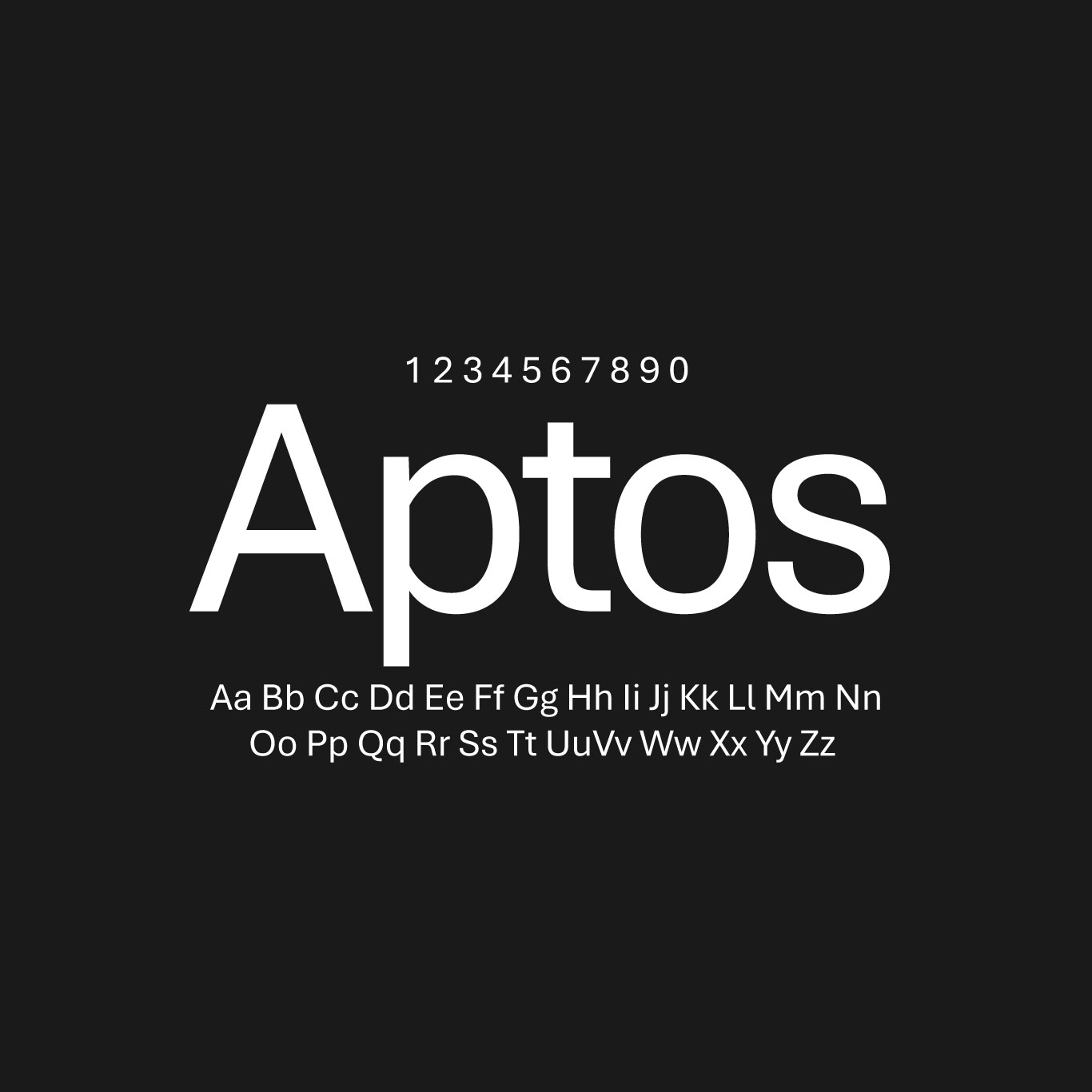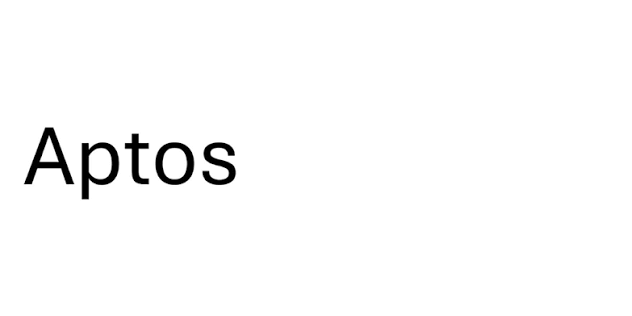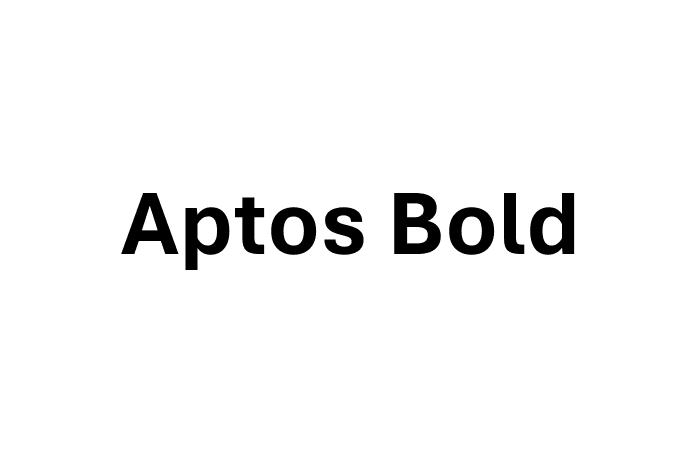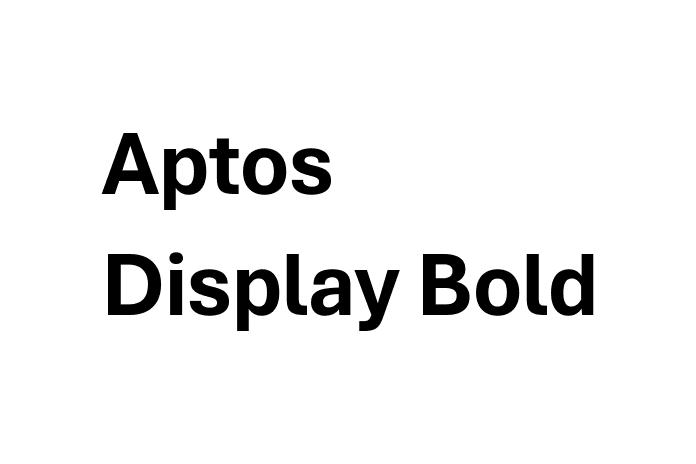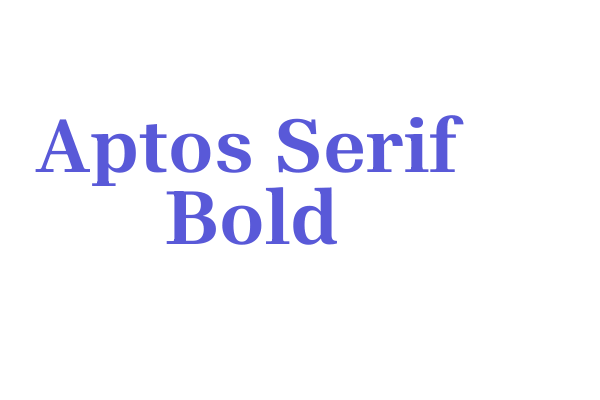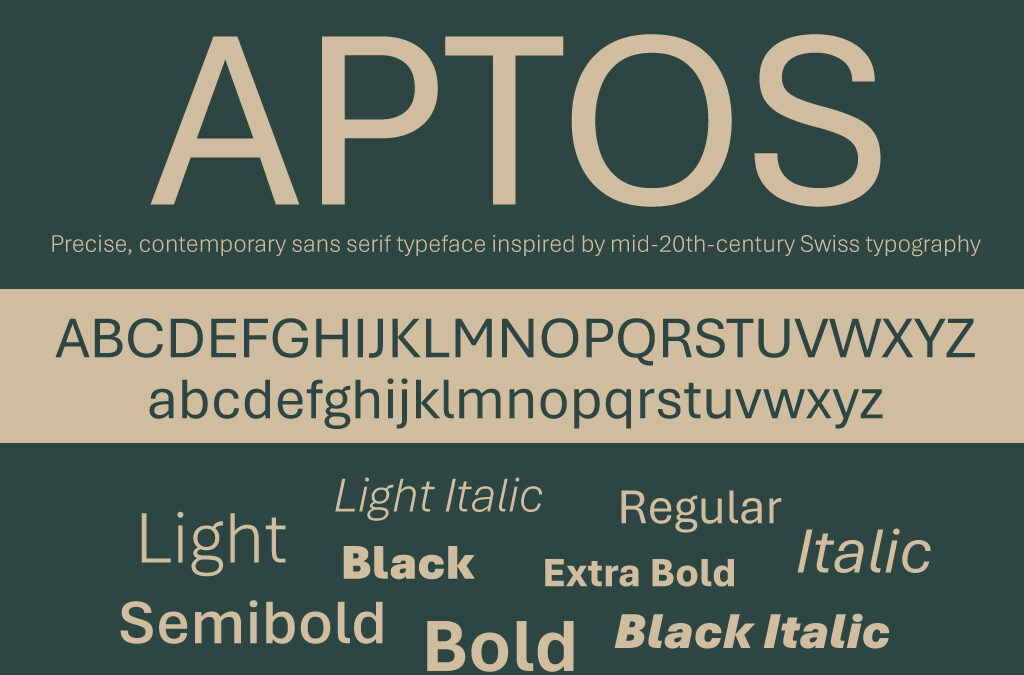
Aptos là hệ phông chữ không chân (Sans-serif) được Microsoft lựa chọn để thay thế cho Calibri, trở thành phông chữ mặc định mới trên toàn bộ hệ sinh thái Office. Với phong cách thiết kế hiện đại, tinh gọn và khả năng hiển thị rõ nét, việc download font Aptos mang lại giải pháp trình bày văn bản chuyên nghiệp cho các kiến trúc sư và nhà thiết kế.
Đặc tính thẩm mỹ và cấu trúc linh hoạt của bộ font Aptos
Các đường nét của phông chữ này sở hữu sự cân bằng giữa tính kỷ luật hình học và cảm giác nhân bản mượt mà, giúp văn bản trở nên dễ tiếp nhận hơn. Việc tải font Aptos Việt hóa giúp người dùng xử lý tốt các dấu thanh tiếng Việt, đảm bảo các ký tự đặc thù phối hợp hài hòa với khung chữ chính mà không gây hiện tượng chồng lấn hay mất nét.
Sự ổn định của Aptos còn thể hiện qua dải biến thể phong phú, đáp ứng đa dạng nhu cầu từ soạn thảo hợp đồng đến trình bày phối cảnh kiến trúc. Khoảng cách giữa các chữ cái được tính toán thông thoáng, giúp mắt người đọc không bị mỏi khi theo dõi các tài liệu thuyết minh dự án dài. Đây là lựa chọn phù hợp cho những ai muốn thể hiện phong cách làm việc đổi mới, chuyên nghiệp và chú trọng vào trải nghiệm thị giác của khách hàng trong các dự án xây dựng hiện đại.
| Phân loại phong cách | Sans-serif / Modern Geometric |
| Số lượng biến thể | Đầy đủ từ Light, Regular, SemiBold đến Black |
| Mục đích phù hợp | Văn bản Office, Website, Bản vẽ kỹ thuật, Branding |
Tư vấn lựa chọn: Aptos đạt hiệu quả thị giác cao khi bạn biết cách tận dụng các biến thể Bold cho tiêu đề chương và Regular cho phần nội dung mô tả chi tiết. Sự tương phản vừa phải của bộ font này sẽ giúp hồ sơ năng lực dự án nhà lắp ghép của bạn trông mạch lạc và hiện đại hơn.
03 Ứng dụng phông chữ Aptos vào hồ sơ kiến trúc thực tế
Nhờ diện mạo khoa học và tính ứng dụng đa năng, việc sử dụng các kiểu chữ từ tải font Aptos mang lại giá trị thực tế cao trong quá trình triển khai dự án hiện đại:
- Trình bày slide báo cáo tiến độ: Sử dụng Aptos giúp các bảng biểu dự toán và sơ đồ mặt bằng trên Powerpoint hiển thị rõ ràng, chuyên nghiệp, tạo ấn tượng tốt về sự cập nhật công nghệ của đơn vị thi công với chủ đầu tư.
- Ghi chú chi tiết trên bản vẽ AutoCAD: Độ rõ nét của Aptos hỗ trợ đắc lực cho kỹ sư khi trình bày các thông số về vật liệu panel, kết cấu khung thép, giúp đội ngũ giám sát tại công trường tra cứu thông tin nhanh chóng và chính xác.
- Hệ thống biển hiệu cho văn phòng container: Những nét chữ hiện đại của Aptos rất ăn ý khi được gia công cắt chữ nổi mica hoặc dán decal nội khu, giúp không gian làm việc toát lên vẻ chỉn chu và tinh tế.
03 Lưu ý trình bày bố cục hiện đại với Aptos download font
Để khai thác hiệu quả vẻ đẹp trung tính và công năng của bộ phông chữ mặc định thế hệ mới này, người thiết kế nên lưu tâm một số lưu ý kỹ thuật sau:
- Kiểm soát khoảng cách dòng: Với cấu trúc chữ hiện đại của Aptos, bạn nên thiết lập khoảng cách dòng thoáng một chút (khoảng 1.4 – 1.5 lần cỡ chữ) để văn bản không bị bết dính, giúp người đọc cảm thấy thoải mái hơn khi tiếp nhận nội dung.
- Phân cấp thông tin bằng độ đậm: Hãy tận dụng biến thể SemiBold của download font aptos cho các đề mục phụ để tạo độ nhấn thị giác mạnh mà không làm cho trang giấy bị cảm giác quá nặng nề như khi dùng kiểu Black.
- Tính đồng bộ trong hệ thống tài liệu: Hãy duy trì sử dụng Aptos xuyên suốt từ hồ sơ báo giá đến slide thuyết trình để tạo nên sự nhất quán trong nhận diện thương hiệu chuyên nghiệp của đơn vị thiết kế và thi công.